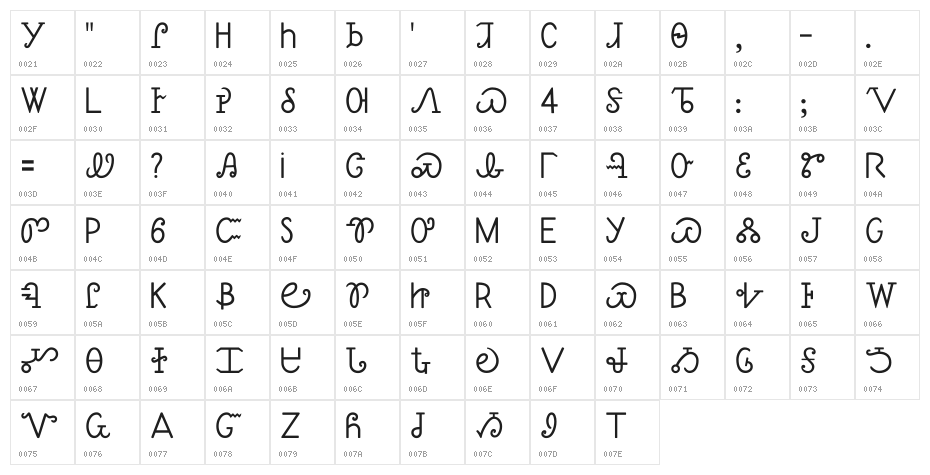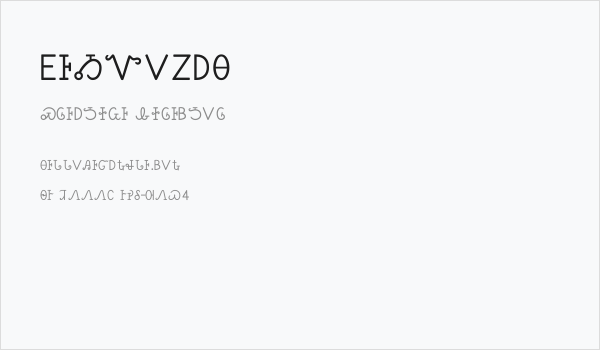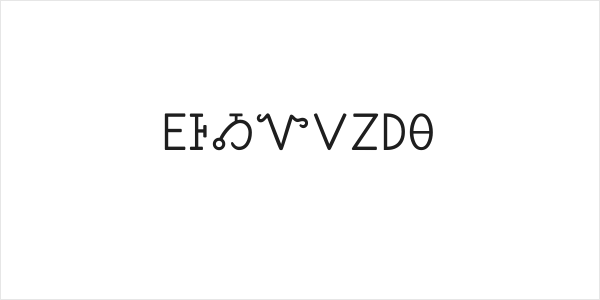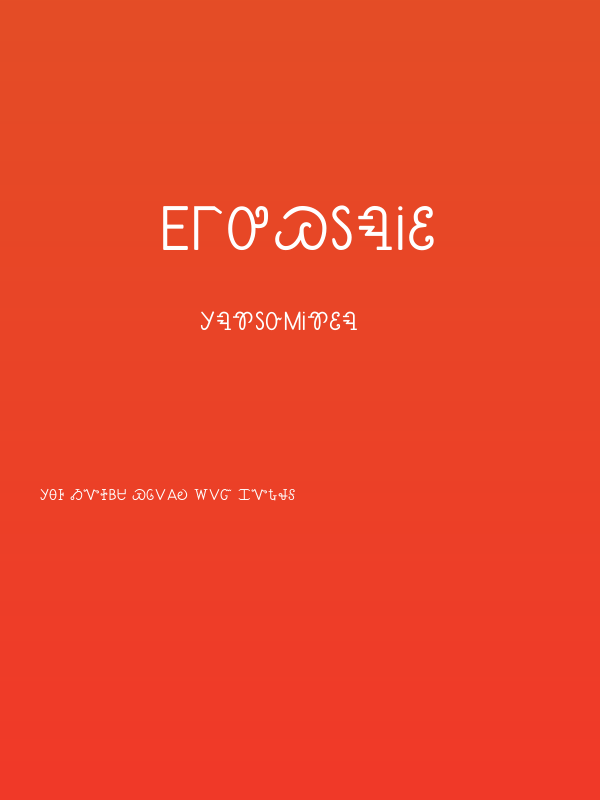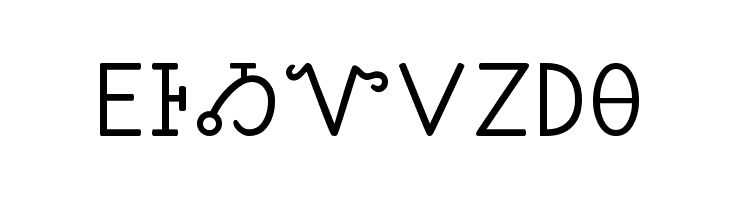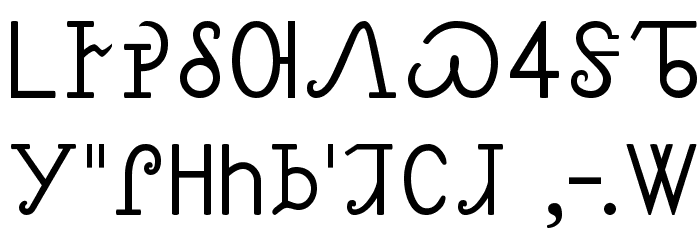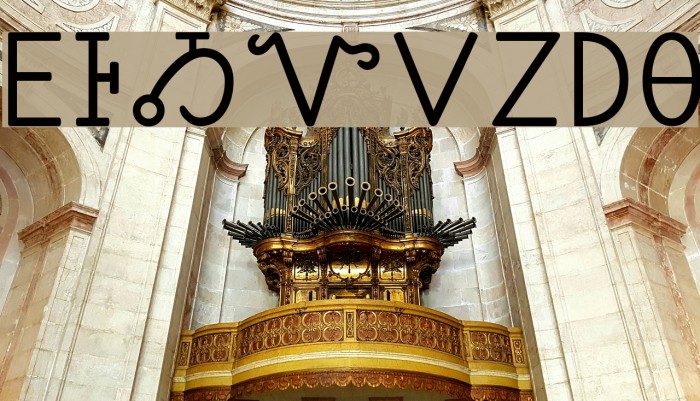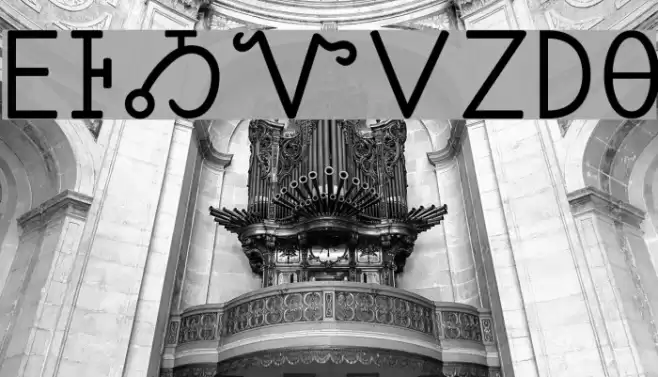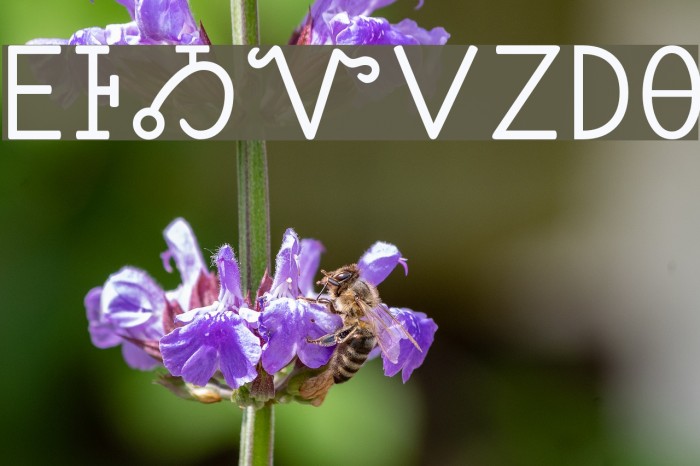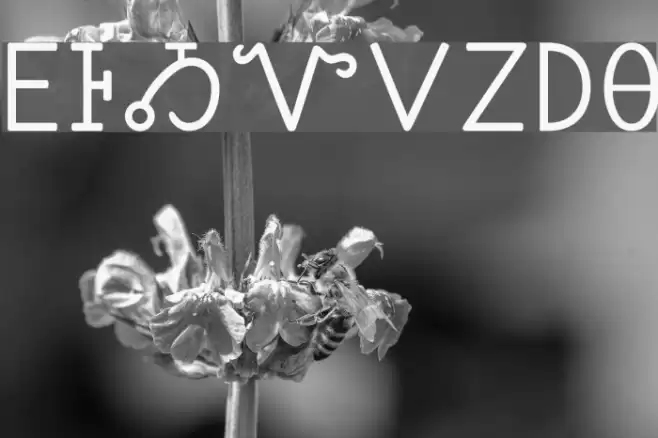
Sequoyah Font
| Caso d'uso | Logos, Educational materials, Cultural projects |
| Progetti proposti | Ideal for educational materials, cultural projects, and historical documentation related to the Cherokee language. |